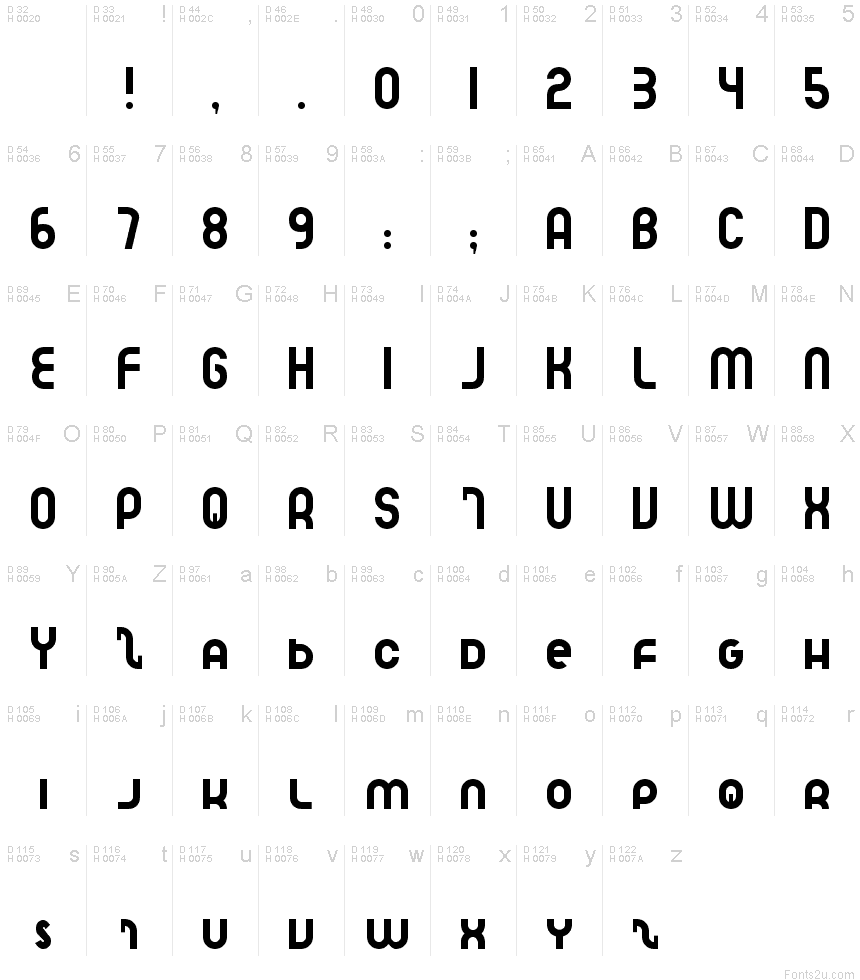
Speedlearn Normal
<p>Speedlearn Normal di SDFonts è un font display moderno dal look sans rotondo e corposo, capace di trasmettere velocità senza sembrare un artificio. Le lettere sono larghe, con angoli morbidi, grandi forme circolari e un ritmo compatto e deciso che spinge le parole in avanti con determinazione.</p>
<p>Funziona bene per flyer tecnologici, branding giovane, grafiche promozionali per app, titoli di poster e packaging in cui serve un tocco audace e amichevole. Essendo un font gratuito, è l'ideale per titoli, copertine e bozzetti di loghi: quelle forme pesanti e arrotondate catturano l'attenzione anche quando il testo è breve.</p>